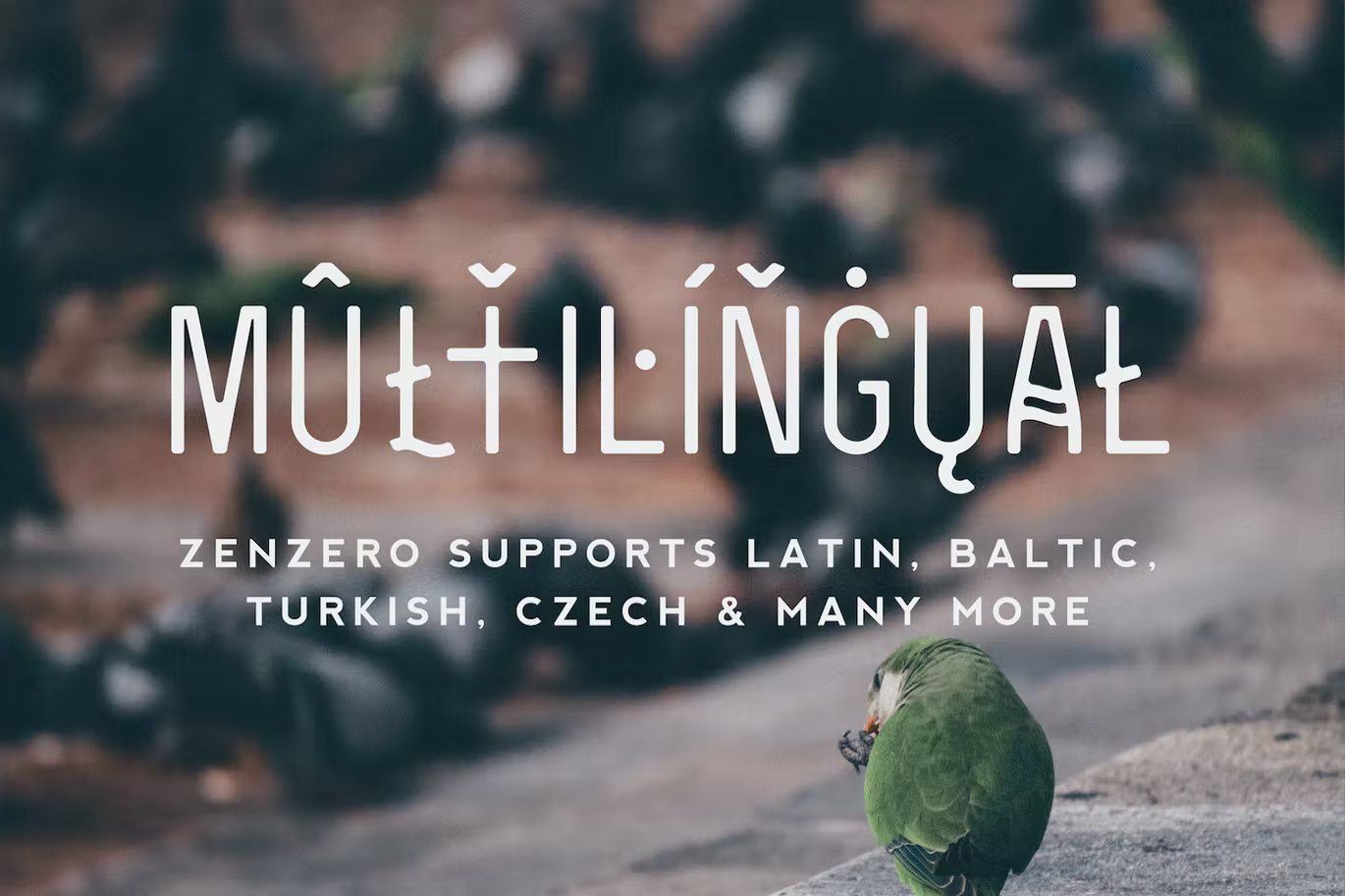
Zenzero Sans Font
Description de Zenzero Sans Font
Zenzero Grotesk San est une police *industrielle qui peut être utilisée de différentes manières. Sa principale vertu est le nombre infini de possibilités d’écrire des mots, des textes ou des paragraphes. Il propose des tonnes de ligatures et de glyphes stylistiques alternatifs, pour un contrôle complet du résultat final.
2 styles de police Opentype Régulier et rond
Langues prises en charge : albanais, catalan, croate, tchèque, danois, néerlandais, espéranto, estonien, philippin, finnois (Suomi), frison occidental, français, hongrois, irlandais, italien, letton, lituanien, norvégien, polonais, portugais, roumain, serbe , slovène, espagnol, suédois, turc, gallois, anglais, allemand